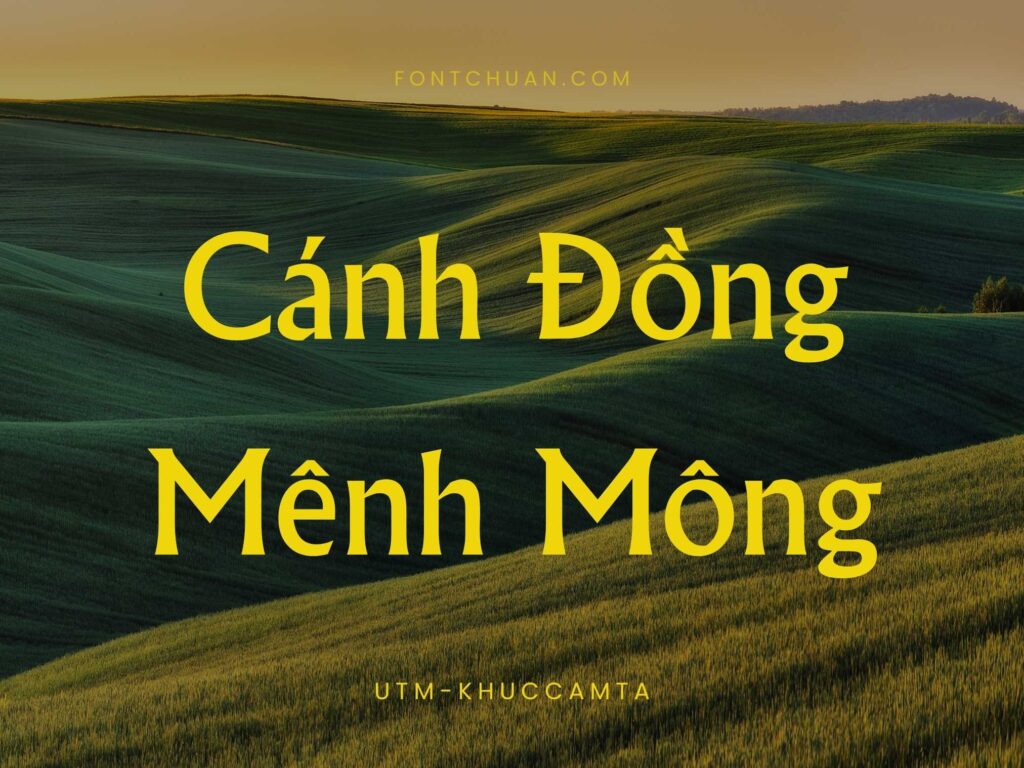
Font UTM Khuccamta Việt Hóa
UTM Khuccamta là một font chữ mang phong cách thư pháp cổ điển, đồng thời mang nét đặc trưng của Font cổ trang, kết hợp giữa sự mềm mại và đường nét mạnh mẽ, tạo cảm giác hoài niệm và đầy nghệ thuật. Font này mang đến vẻ đẹp truyền thống, thường được sử dụng trong các thiết kế mang đậm dấu ấn văn hóa và nghệ thuật. Font đã được Việt hóa bởi Thiên Minh, hỗ trợ đầy đủ tiếng Việt cùng hơn 200 ngôn ngữ khác, giúp mở rộng khả năng ứng dụng. Thành viên của Font Chuẩn đã sưu tầm và giới thiệu font này nhằm đáp ứng nhu cầu bạn đọc, cung cấp nguồn tham khảo chất lượng và ứng dụng thực tế vào các dự án thiết kế.
Về đặc điểm thiết kế, UTM Khuccamta có các đường nét uốn lượn, độ tương phản cao và phong cách thư pháp đặc trưng. Font này phù hợp với nhiều ứng dụng như thiết kế tiêu đề, logo, bìa sách, poster, biển hiệu và các ấn phẩm nghệ thuật khác. Các ngành nghề như quảng cáo, ẩm thực, thiệp cưới và giáo dục có thể tận dụng font này để tạo nên sự khác biệt và thu hút trong các sản phẩm thiết kế